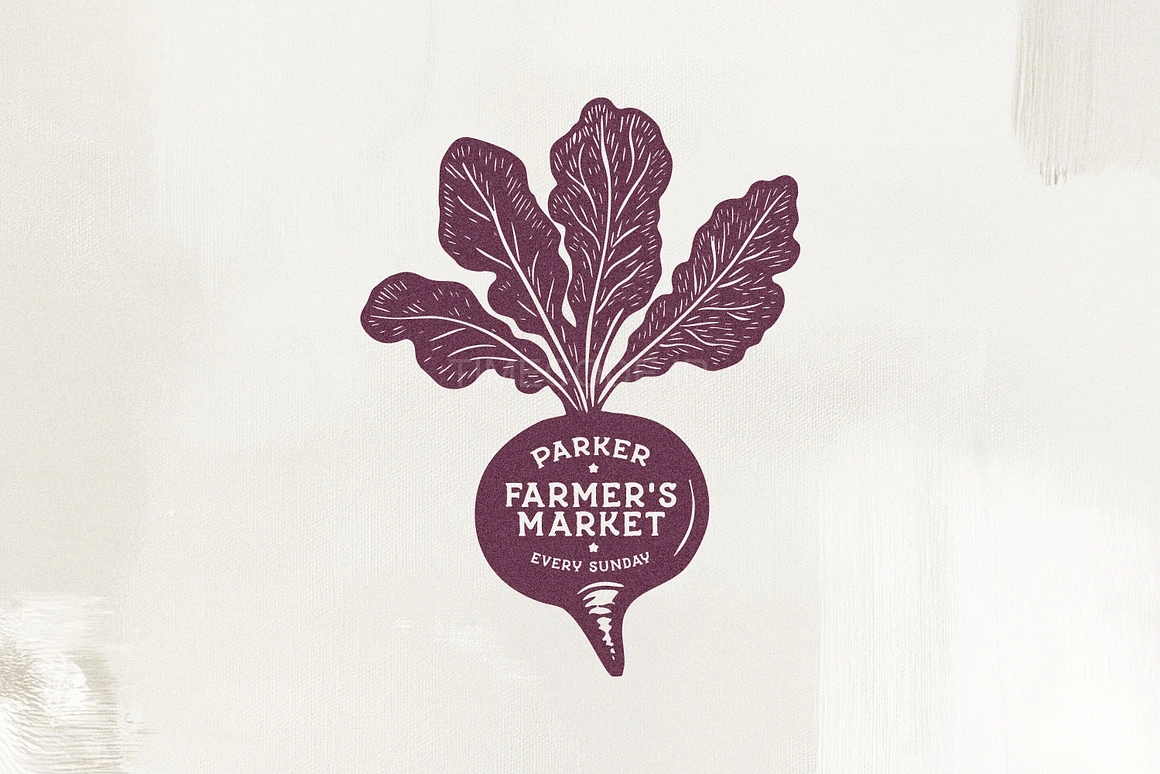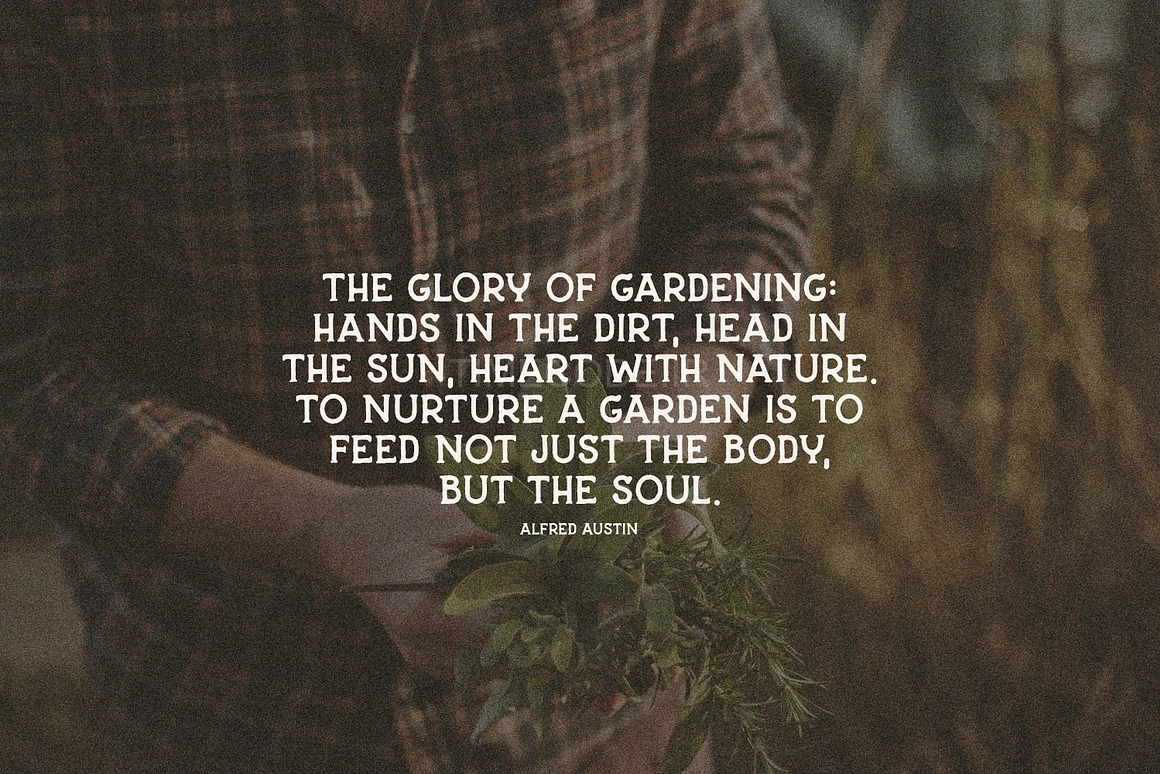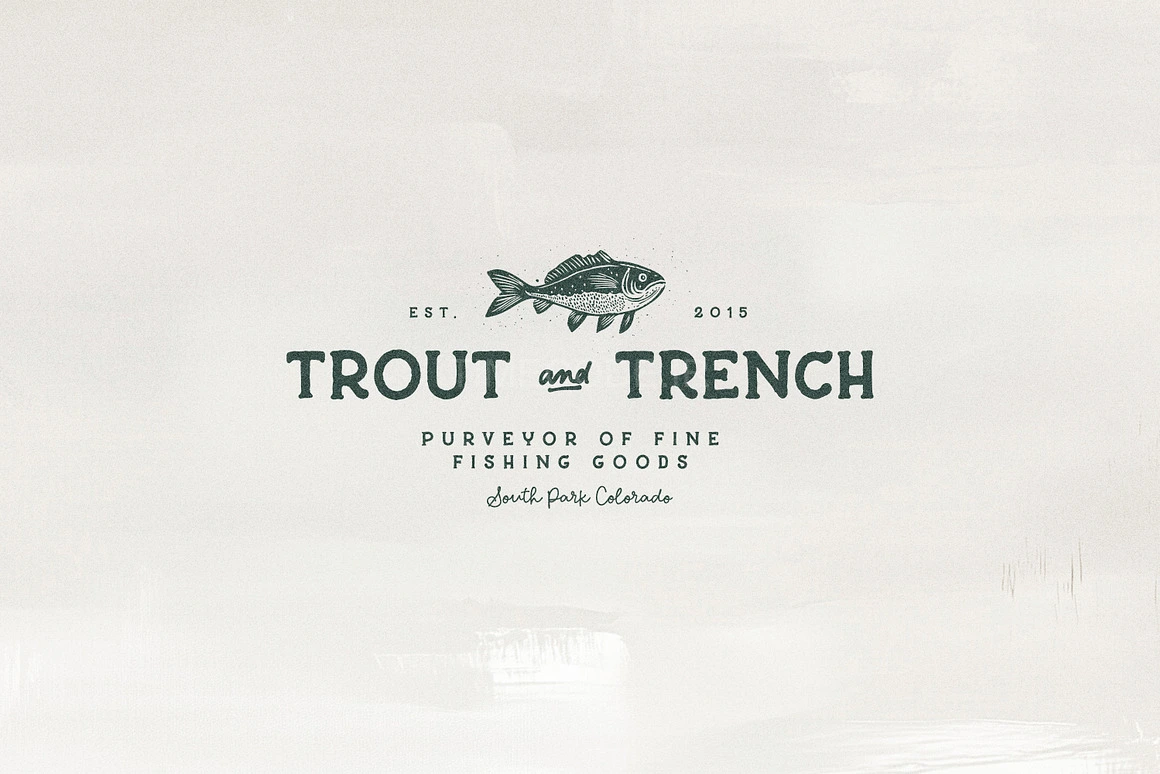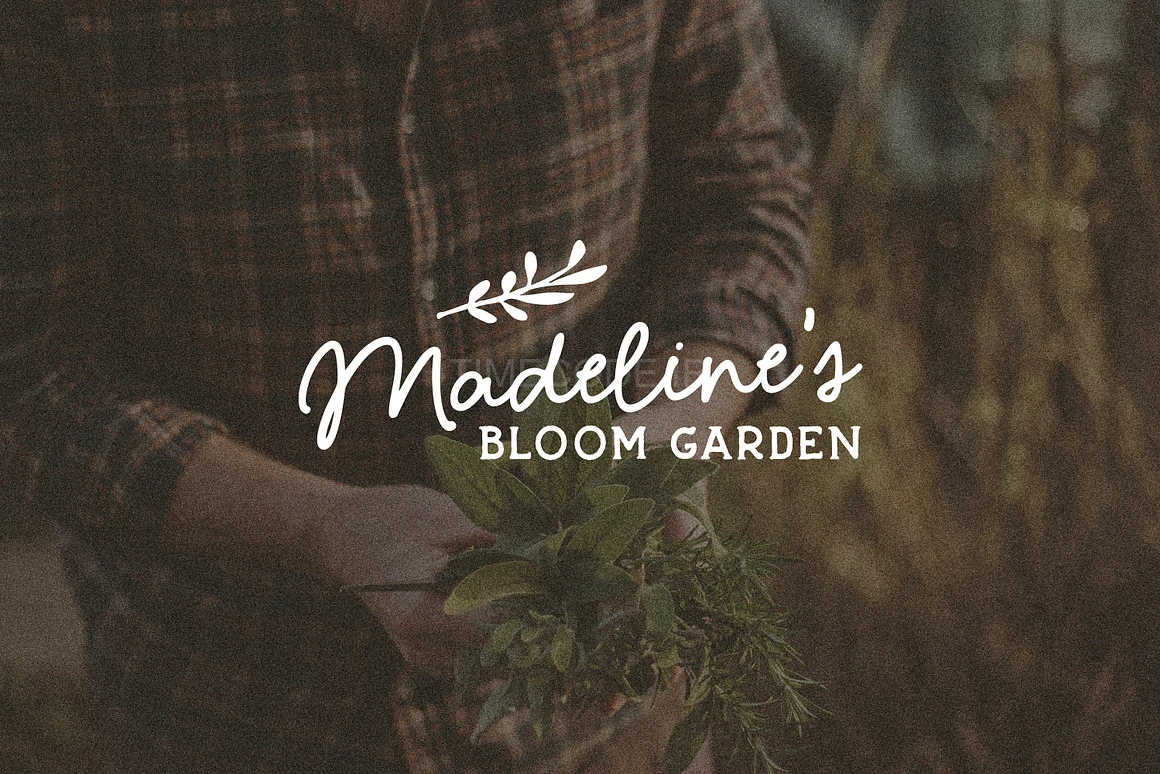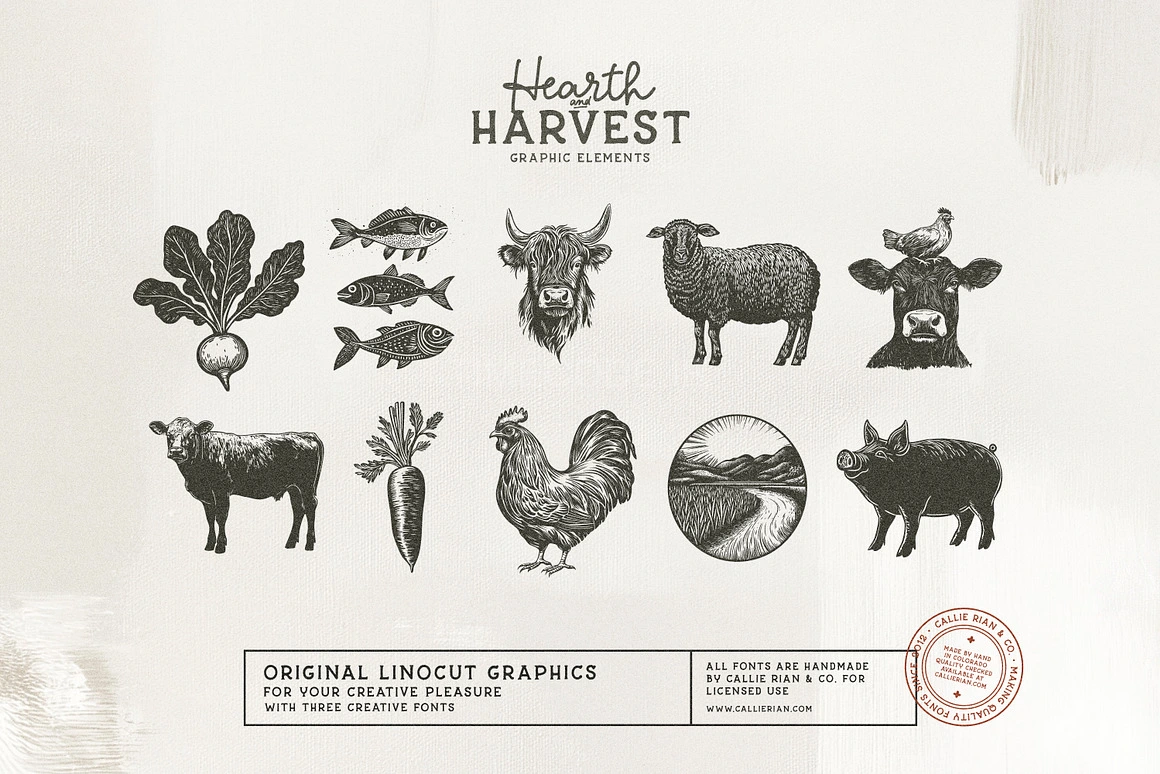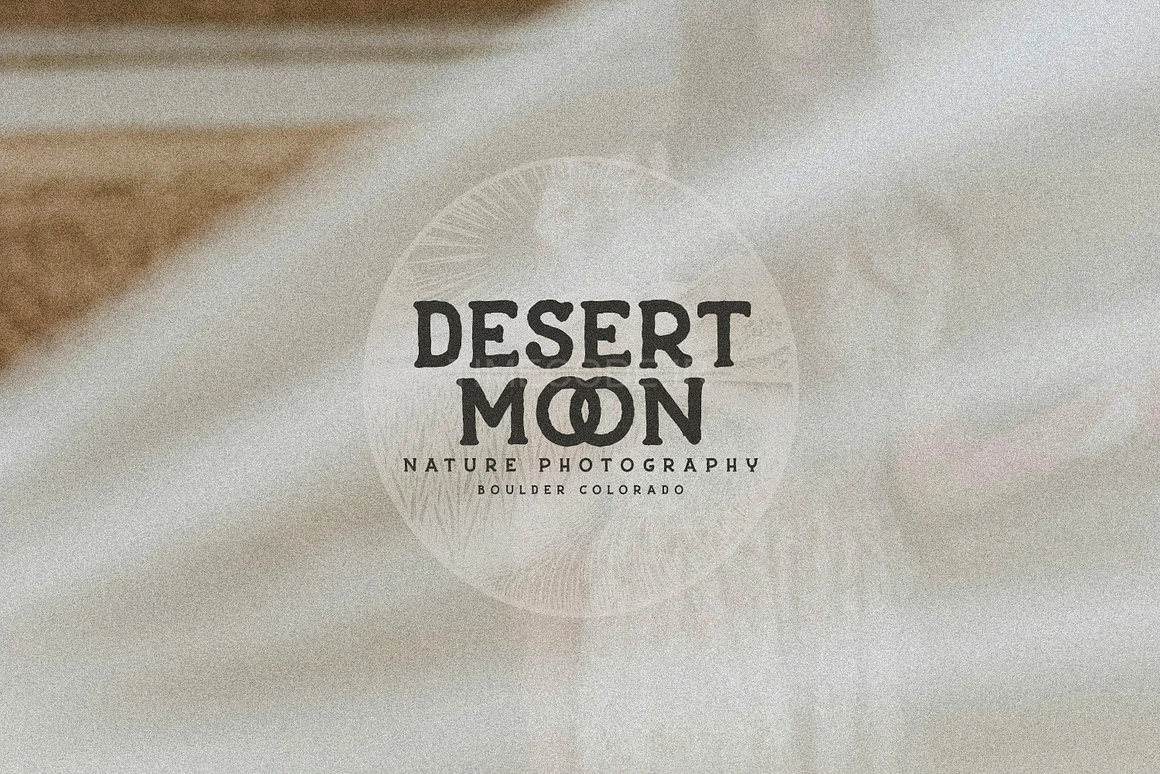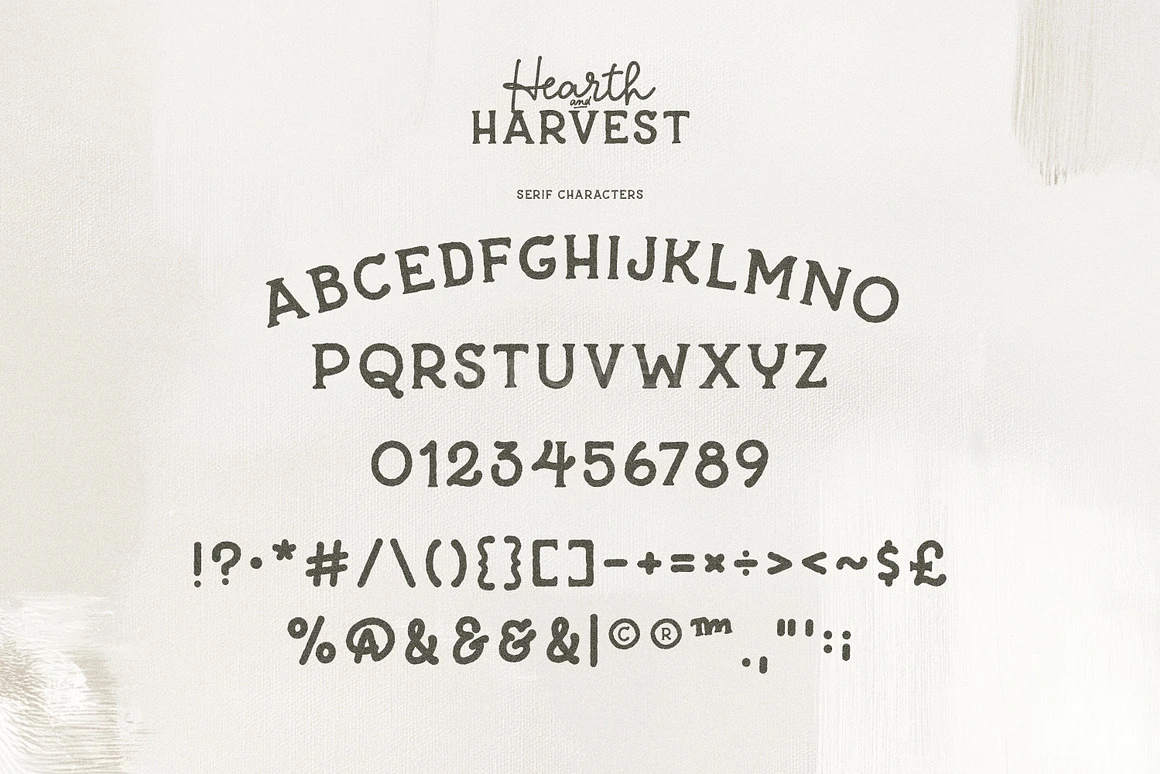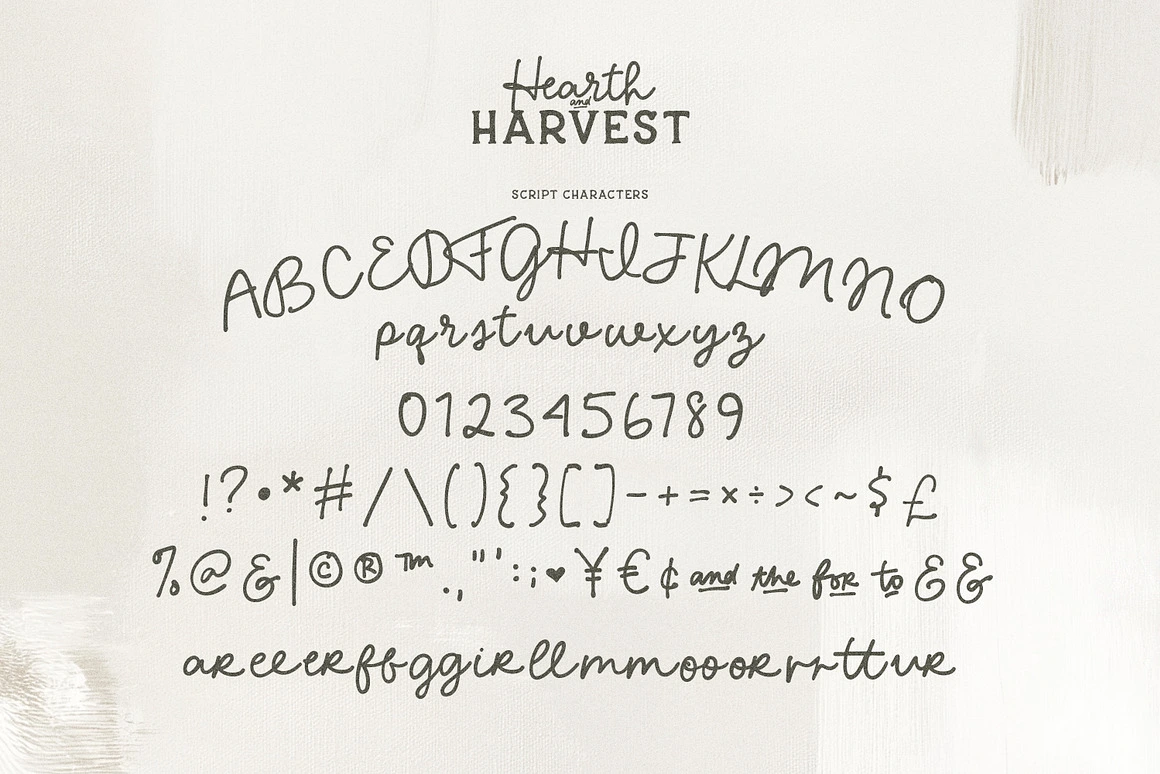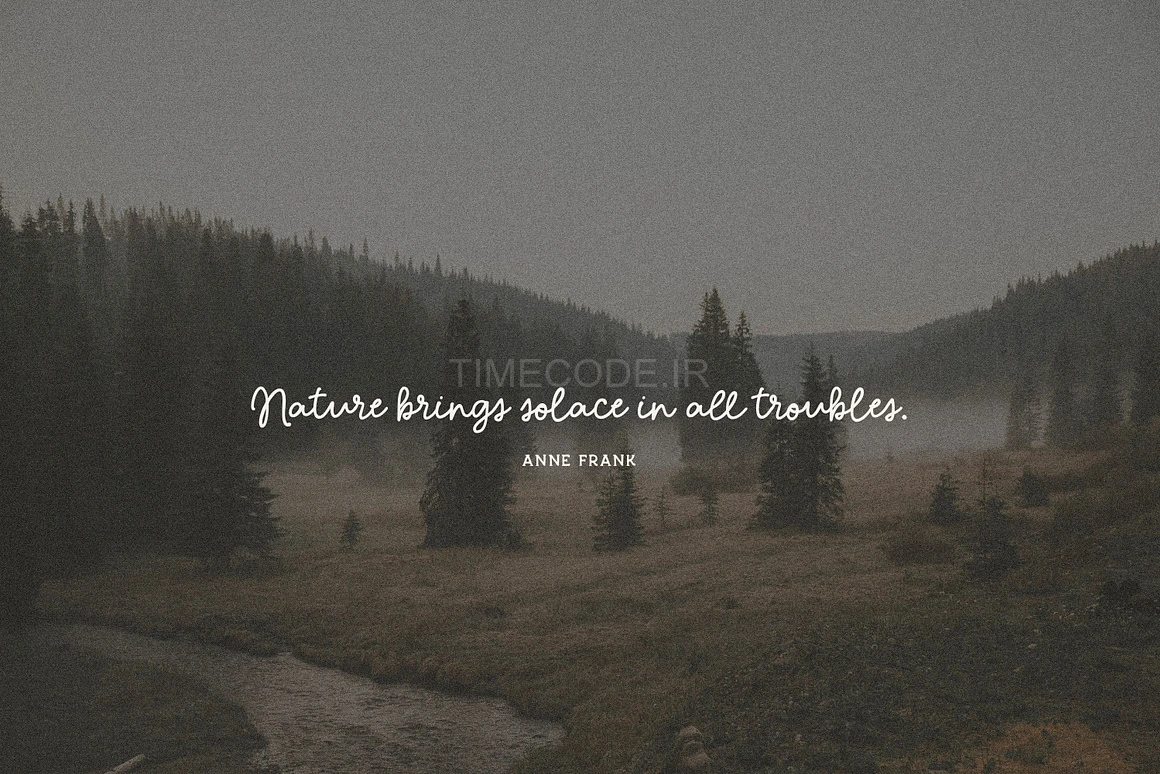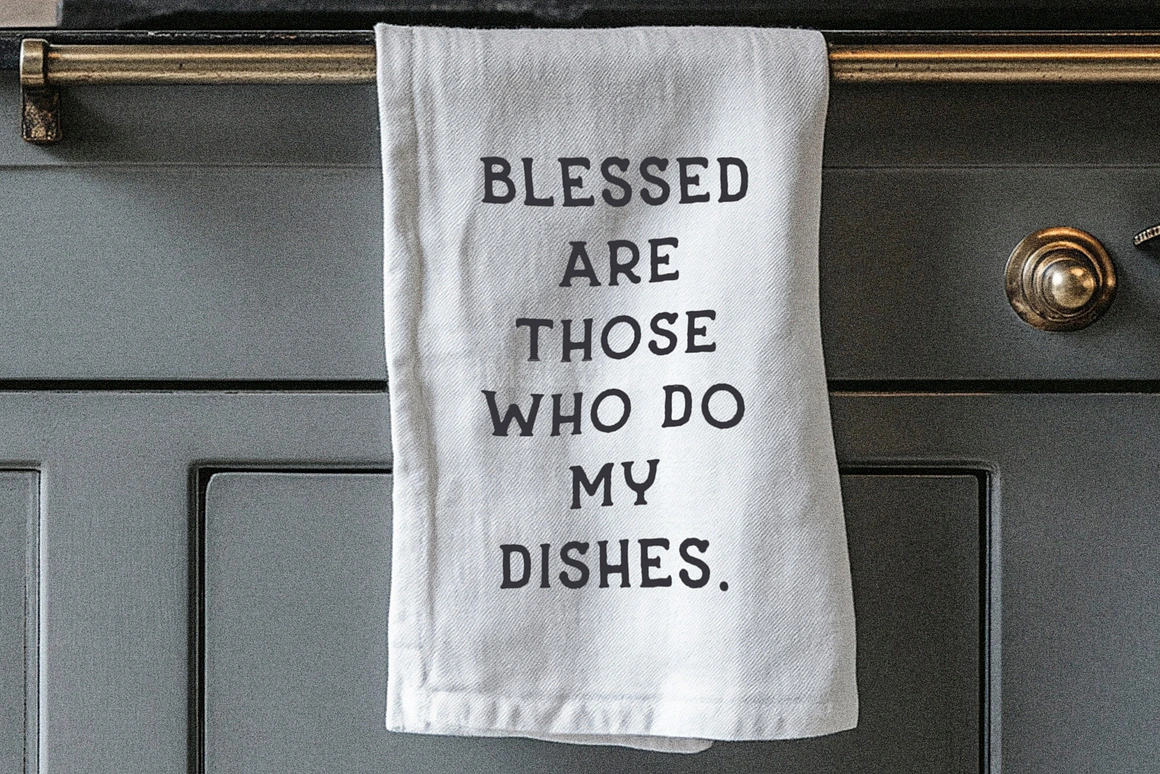
Hearth & Harvest، یک خانواده فونت سریف و اسکریپت دست‌نویس با حسی روستیک. از دو نسخه سریف (معمولی و ضخیم) و همچنین یک فونت اسکریپت ساده برای لوگو، نقل قول، پوشاک، مجلات و موارد دیگر لذت ببرید! به علاوه، مجموعه‌ای از گرافیک‌های linocut (چاپ لینو) نیز برای تکمیل فونت‌های جذاب جدید شما گنجانده شده است. Hearth & Harvest یک مجموعه کامل برای همه چیز، از مقالات گرفته تا بسته‌بندی، است.
• فقط شامل کاراکترهای انگلیسی
• لطفاً توجه داشته باشید که این فونت‌ها دست‌نویس هستند، بنابراین لبه‌های آن‌ها ممکن است کمی نامنظم باشد. نسخه اسکریپت با دستگاه‌های Cricut یا Silhouette کار می‌کند، اما من تلاش برای برش فونت‌های سریف روستیک را پیشنهاد نمی‌کنم.
• پشتیبانی از زبان‌های بین‌المللی وجود ندارد.
Introducing Hearth & Harvest, a hand drawn Serif & Script family with a rustic touch. Enjoy two serif versions; regular and bold, as well as simple script for logos, quotes, apparel, magazines and more! Plus, I’ve included a set of linocut graphics to compliment your charming new fonts. Hearth & Harvest is a one-stop-shop for everything from editorials to packaging.
- English Characters Only
- Please Note these fonts are handwritten , so the edges might be a little irregular. The Script Version will work with Circuit or Silhouette, but I wouldn’t try and cut the Rustic Serifs.
- No International Language Support